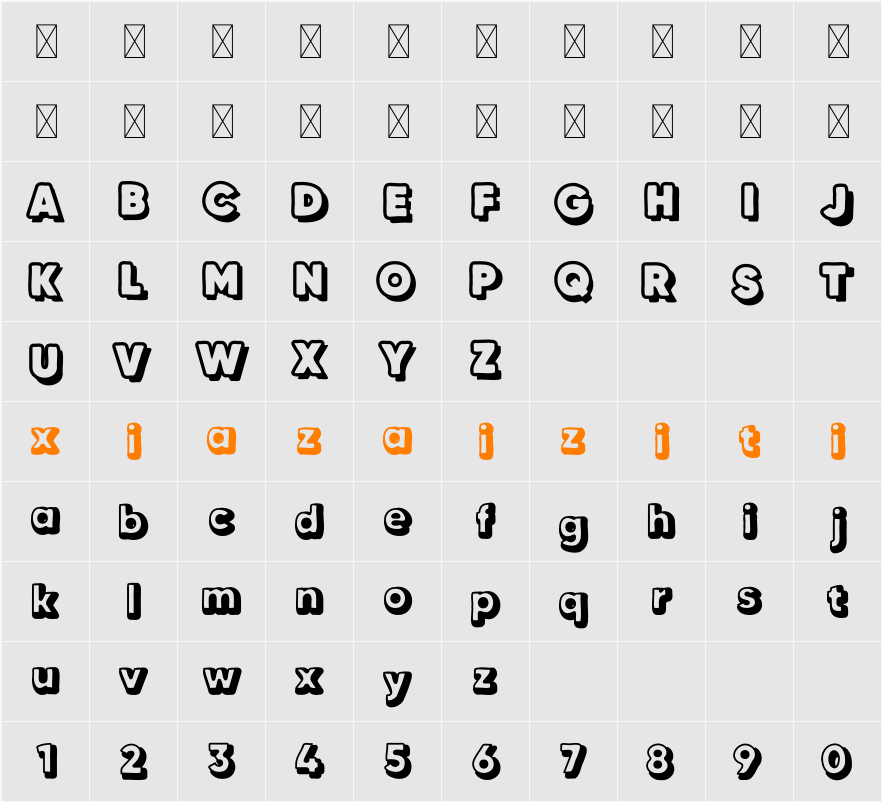
Alchemist Whiteboard Drop Shadow
Alchemist Whiteboard Drop Shadow,这款字体结构工整、笔画清晰,兼顾美观与易读性,适用于标题、正文、海报、包装、LOGO 等多种场景。字形优雅稳定,风格百搭耐看,适配日常排版与创意设计,让文字呈现更舒适、更具质感。Alchemist Whiteboard Drop Shadow一笔一画,皆是细节,以均衡的比例、流畅的线条打造舒适视觉体验,字形端正大气,风格简约现代。无论是商业设计、品牌宣传还是日常排版,都能轻松驾驭,让文字更有格调与力量。Alchemist Whiteboard Drop Shadow字体下载。
• 制造商: Digital Alchemist Media Productions
• 设计师: Ardi Alemi